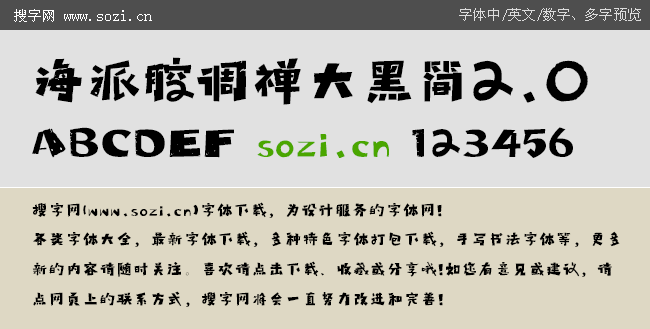
海派腔調(diào)禪大黑簡2.0
搜字網(wǎng)提供一款海派腔調(diào)禪大黑簡2.0中文字體下載,海派腔調(diào)禪大黑簡字體是一款左粗右細(xì)、整體效果非常出眾的簡體中文字體,適合應(yīng)用于廣告設(shè)計(jì)、名片設(shè)計(jì)、包裝印刷、產(chǎn)品設(shè)計(jì)等應(yīng)用。